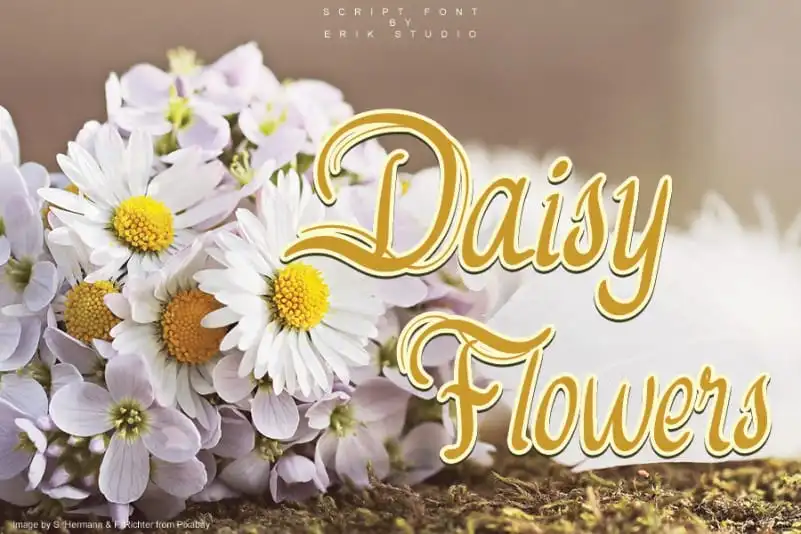
Daisy Flowers Script Font – Fonte Grátis
Daisy Flowers Script Font
Daisy Flowers Script Font é uma fonte tipográfica escrita a mão que transmite romantismo e delicadeza. As letras têm um toque quase encantador, dançando sobre o baseline de texto. É perfeitamente adequada para criar cartas de casamento ou outros designs que precisam de uma personalização romântica e única. Esta fonte é ideal para qualquer projeto gráfico que busque adicionar um ar delicado e alegre à sua obra, seja para escrever cartas de amor, convites de casamento ou até mesmo mensagens de aniversário. Seja você designer gráfico ou ilustrador digital, Daisy Flowers Script Font será um recurso valioso para dar vida às suas criações, adicionando nuances delicadas e românticas ao seu design.